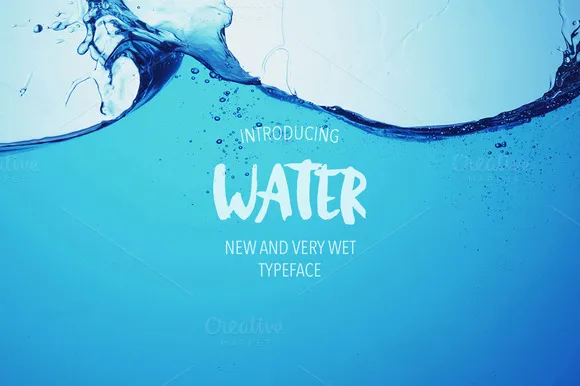
Water Font – Download Grátis
Esta é uma maravilhosa fonte criada à mão com amor! Aproveite para usar a Water Font em diversos projetos, desde criações fashion até convites e cartões de visita. É perfeitamente adaptável aos mais variados usos, como design gráfico e muito mais. Como designer, Hamilton nos presentou com uma fonte única que se encaixa perfeitamente na categoria de Brush Fonts, tornando-a um recurso valioso para qualquer projeto onde o estilo artesanal seja desejado.